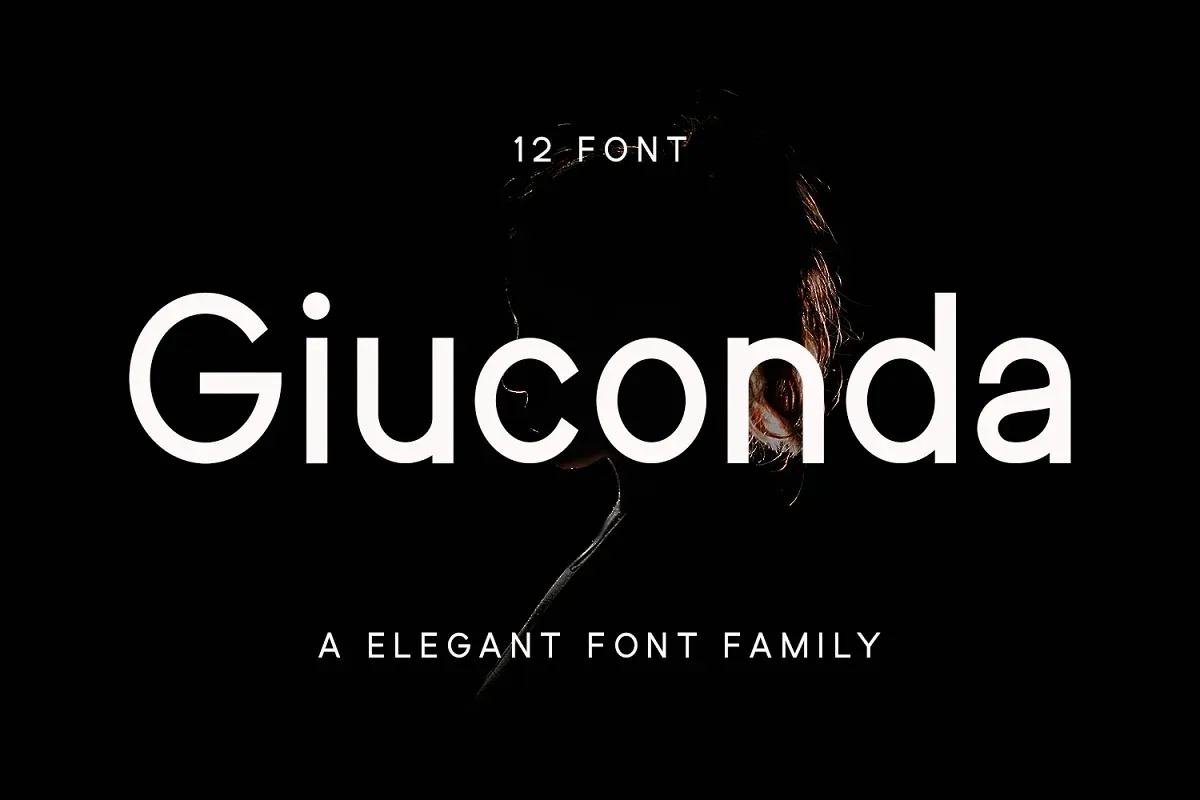
A Giuconda Font é uma tipografia sans-serif que traz um vislumbre fresco e contemporâneo para qualquer projeto design. Essa fonte oferece um aspecto mais limpo e geométrico, preservando a essência e estrutura de um antigo tipo de sans serif do início do século vinte, mas com uma aparência renovada, clara e atualizada. Seja para rótulos em embalagens ou letras no layout de uma revista, a Giuconda é perfeita para tornar seu design mais moderno. Ideal para designers que valorizam um look minimalista e clean, esta fonte está à procura de adicionar uma nova dimensão visual aos seus projetos visuais. Combinada com sua elegante simplicidade, a Giuconda proporciona uma experiência de leitura fácil e acessível ao usuário final. Esta é uma excelente opção para qualquer projeto que deseja se destacar através de um design minimalista e atualizado.